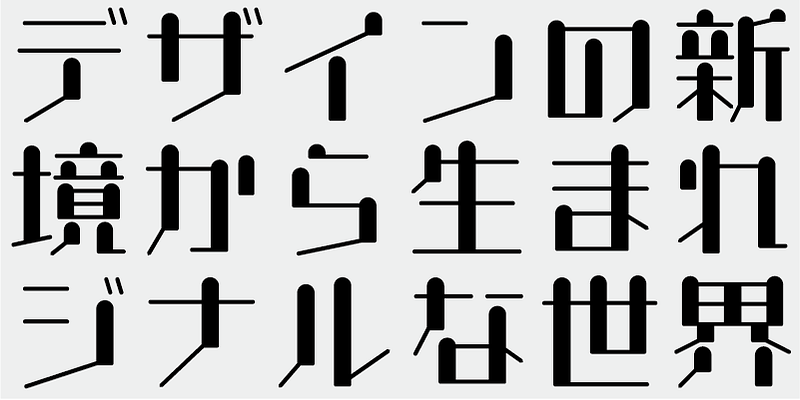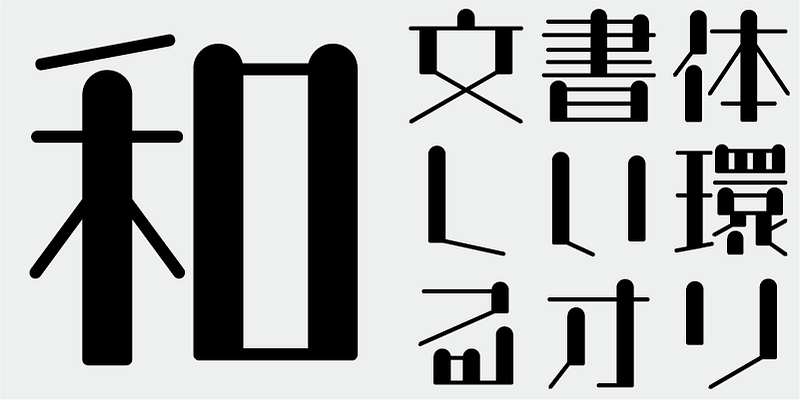
Esta fuente contiene 2286 caracteres de la lista Joyo Kanji y de los caracteres Jinmei-yo Kanji, así como 206 caracteres adicionales que incluyen caracteres kana, signos de puntuación y caracteres latinos, etc.
En la producción de fuentes japonesas de hoy en día, los 7000 caracteres del estándar JIS se consideran esenciales. Pero, ¿todas las fuentes realmente necesitan 7000 caracteres? En la época de la fotocomposición, se necesitaban muchos menos caracteres. FONT1000, un grupo de diseñadores de tipos de letra independientes, comenzó con esa sencilla pregunta. Hemos seleccionado el mínimo de 1000 caracteres kanji (ideográficos) necesarios para la composición tipográfica en japonés y nos hemos esforzado en crear tipos de letra y fuentes de forma activa para admitirlos. Este conjunto de 1000 caracteres kanji se seleccionó utilizando datos de frecuencia de caracteres recopilados por empresas de periódicos, editoriales, organizaciones de investigación lingüística, etc., y también incluye caracteres silábicos kana y signos de puntuación. FONT1000 se formó en 2001 con 25 diseñadores y 25 tipos de letra. Hoy tenemos 130 tipos de letra y hemos crecido hasta incluir casi 40 miembros, lo que hace posible trabajar con tipos de letra con más caracteres.